Font personalizzati con TypeFace
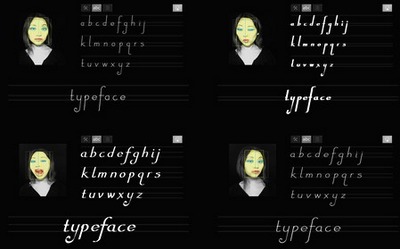
Scrivere è il vostro lavoro o la vostra passione? Se utilizzate quotidianamente il computer, allora sarete sempre alla ricerca di vari font da inserire all’interno dei vostri commenti. Vi piacerebbe trovare dei font da installare immediatamente all’interno del vostro sistema operativo? Le risorse disponibili online dedicate ai font sono innumerevoli ma noi abbiamo trovato uno strumento gratuito per voi.
Vi presentiamo Typeface, uno strumento davvero innovativo, che vi permetterà di creare dei font diversi a seconda della vostra mimica facciale. Non ci crede? Invece è assolutamente possibile! TypeFace si presenta come un programma gratuito ed utilizzabile sia su OS Windows che su Mac che, così come già accennato, permetterà di tramutare le espressioni del proprio volto in un insieme di font personalizzati.
Per utilizzare il programma, dovrete utilizzare una web cam che inquadrerà il proprio volta e darà il via alla creazione del font relativo alla vostra mimica. Dopo una prima installazione TypeFace sarà in grado di riconoscere la distanza tra occhi, naso, bocca e modificando la forma delle lettere in base alla vostra fisionomia.
Tutti i font ottenuti potranno poi essere esportati ed utilizzati dopo il processo di trasformazione. Uno strumento davvero innovativo, che vale la pena provare almeno una volta, vista la sua originalità. Pensate alla possibilità di creare font davvero personalizzati che nessuno ha, questa si che è una bella iniziativa vero?